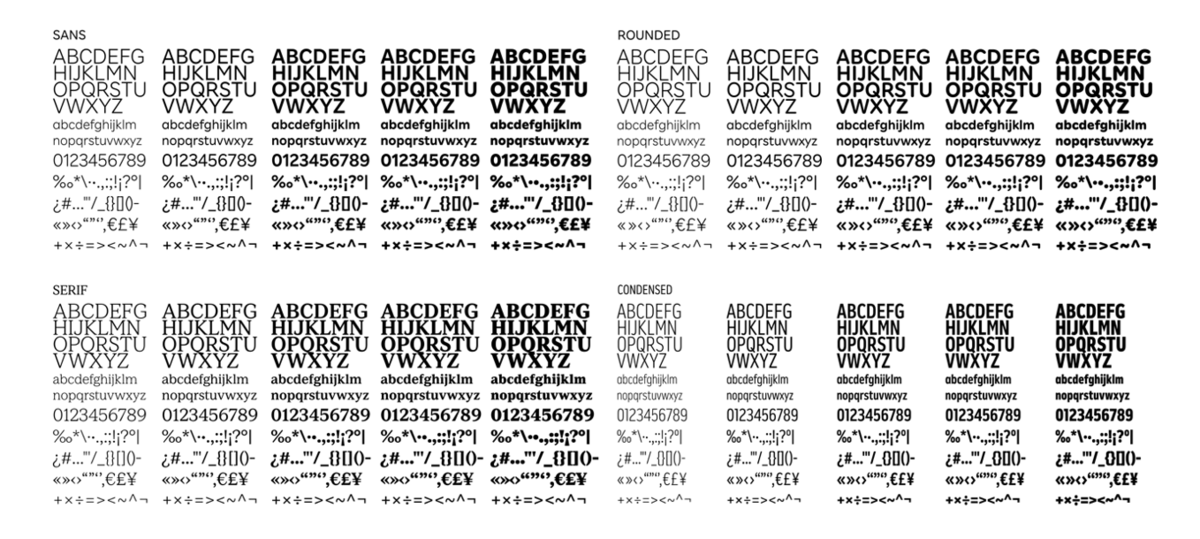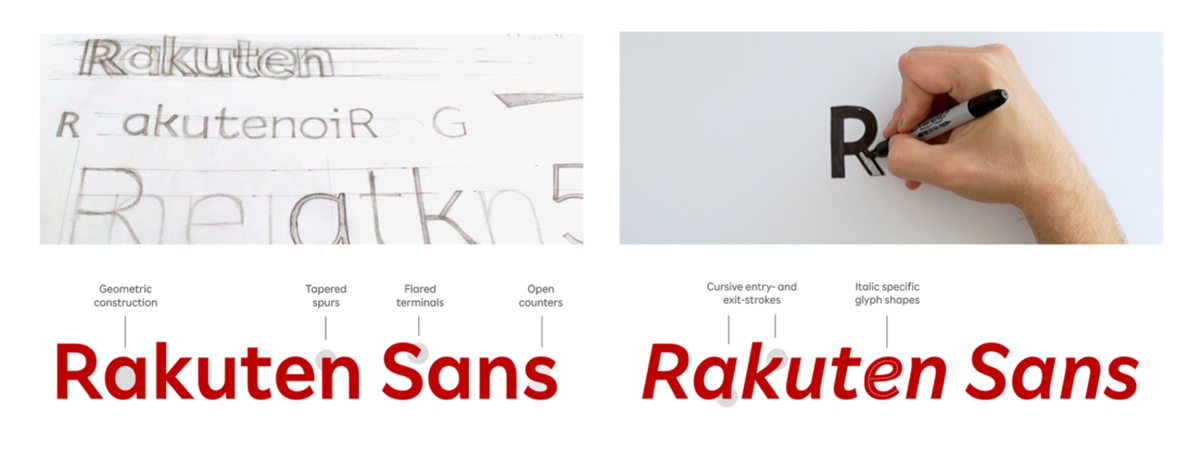
楽天が新しいグローバルフォント「Rakuten Sans」「Rakuten Serif」「Rakuten Rounded」「Rakuten Condensed」を発表!新たに開発した4種類のフォントにより、グループブランドの統一性と多様性の双方を表現可能に
楽天は、ウェブサイトやアプリ、その他制作物等に用いるグローバルフォントのデザインを一新し、新フォント4書体「Rakuten Sans」「Rakuten Serif」「Rakuten Rounded」「Rakuten Condensed」を開発したことを2020年7月2日に発表した。
新フォントは国内外における楽天グループのサービスや社内外向け資料で、順次適用していく。
楽天は、Eコマースをはじめ、フィンテック、デジタルコンテンツ、通信など、多岐にわたる分野で70以上のサービスを提供しているほか、近年では海外のスポーツチームとのパートナーシップ契約を通じて、ユーザーや社会に向けて様々なメッセージを発信している。
2018年6月には、新しいステージに向けた挑戦への決意を込めてグローバル統一ロゴのデザインを一新し、国内外においてブランドを強化してきた。
こうした中、ウェブサイトやアプリ、その他制作物で用いるフォントにおいても、既存のブランド資産との一貫性を保ちながら、各サービス等の多様性やユニークさを表現できるよう、今回、新フォントを開発した。
楽天が今回開発した4種類のフォント「Rakuten Sans」「Rakuten Serif」「Rakuten Rounded」「Rakuten Condensed」
楽天のチーフクリエイティブディレクターでフォント開発を監修した佐藤可士和氏は、
「フォントは企業のブランドを表現する上で、非常に重要なアセットになります。今回、楽天のロゴの骨格をベースに、4種類の異なる書体を用意しました。用途に応じて最適なフォントを用いることで、ブランド表現の幅が広がり、ユーザーに対しても、より伝わりやすい形で、メッセージをお届けできると考えています」
とコメントしている。
また、これまで多くの企業フォントの開発を行い、今回のフォント開発にも携わったロンドン(イギリス)のフォントデザインスタジオDalton Maag社ChairmanのBruno Maag氏は、
「楽天の新たなオリジナルフォントの開発に携われたことを大変嬉しく思います。新フォントのデザインでは、トーン・オブ・ボイス(語り口・調子)に統一性をもたせることで、楽天というブランドの力強くエネルギッシュなイメージを表現しています。一方で、表現の幅をもたせた4種類のフォントを用意することで、楽天のビジネス領域やサービスの多様性に対応しています。このフォントが今後の企業活動に役立つことを願っています」
とコメントしている。
楽天では今後も、様々なブランド資産の開発、ブランディングの強化により、グローバルにおけるグループブランド価値の向上を図るとともに、イノベーションを通じて人々の暮らしをより豊かで便利なものにしていく挑戦を続けていくと発表している。
楽天の新フォント「Rakuten Sans」「Rakuten Serif」「Rakuten Rounded」「Rakuten Condensed」の特徴
基本形となる「Rakuten Sans」は、楽天のロゴを骨格のベースとしており、文字サイズが小さくても高い判別性と可読性を保てるように工夫している。
(上)文字の骨格を検証するためのデッサン(下)最終的な「Rakuten Sans」とその特徴
「Rakuten Sans」に加えて、上品さを表現する「Rakuten Serif」、楽しさや可愛らしさを表現する「Rakuten Rounded」、力強さを表現する「Rakuten Condensed」の計4種類・各5ウェイト(文字の太さ)のフォントセットを開発した。
新フォントは英語、スペイン語、フランス語、ポルトガル語、ドイツ語、イタリア語、ルーマニア語、オランダ語、カタルーニャ語、スウェーデン語、デンマーク語、フィンランド語、ノルウェー語(ブークモール+ニーノシュク)、ウェールズ語、ルクセンブルク語、アイスランド語合計16言語に対応している。